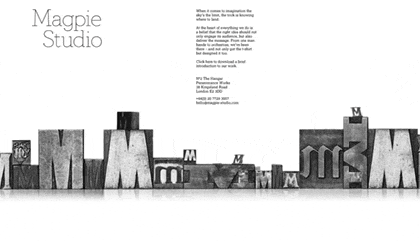
Magpie Studio | Un book en ligne? ou en pdf to download?
Le site de Magpie (prononcez Magpy) Studio se trouve ici. Tout d’abord un constat, de plus en plus de studios préfèrent faire une page d’accueil (en flash ou html) et renvoyer leurs visiteurs vers un PDF de leur book à télécharger. Sincèrement je crois que c’est une erreur. Mon expérience (d’)utilisateur, mes rencontres avec de nombreux D.A. d’agences, et des clients annonceurs me montrent chaque jour que cette pioche est la mauvaise.
Les gens n’aiment pas télécharger un book ou portfolio. Je ne dis pas qu’ils ne le font jamais. La preuve, me suis intéressé à cette frise de typos en plomb qui m’a rappelé l’extraordinaire introductions des JO de Pékin, où l’on voyait, ces centaines de danseurs, nous remémorer, que ce pays de plus d’un milliard d’âmes, a tout de même inventé le caractère plomb, bien avant notre très sympathique Johannes Gutenberg.
Donc cette frise, qui me fait souvenir aussi ce travail remarquable, que Lou Dorfsman, a commandé à Herb Lubalin pour le hall de la CBS… oui forcément je ne pouvais qu’aller plus loin par curiosité légitime. Mais je reste persuadé, que nombre de visiteurs, n’ont pas cette démarche. L’image de cette frise ne suscite en soi aucun émerveillement, une série de lettres en volumes, posées ou photoshopées côtes-à-côtes, et ne serait-ce mon système de référent-mémoriel très particulier, très orienté typo et culture typographique, je n’aurais sans doute pas téléchargé le book de cette jeune agence.
Sur le contenu du book, je n’ai pas grand chose à dire. De l’esprit, des idées, une bonne intelligence de design strategy et sans doute encore beaucoup, beaucoup d’expérience à moissonner pour faire correspondre un discours un peu pompeux avec des résultats un peu limités.
Pour autant, ce qui me frappe une fois de plus, est la nature de mes propres sensibilités qui me portent naturellement à explorer les sites où l’on évoque la typographie comme s’il s’agissait d’éléments muséographiques d’un autre temps. Bon sang. La typo, c’est aujourd’hui, plus vivant que jamais. Et les marques comme me disait Christophe Badani récemment ont plus que jamais besoin de se distinguer au milieu du foisonnement des identités de plus en plus farfelus et anecdotiques.